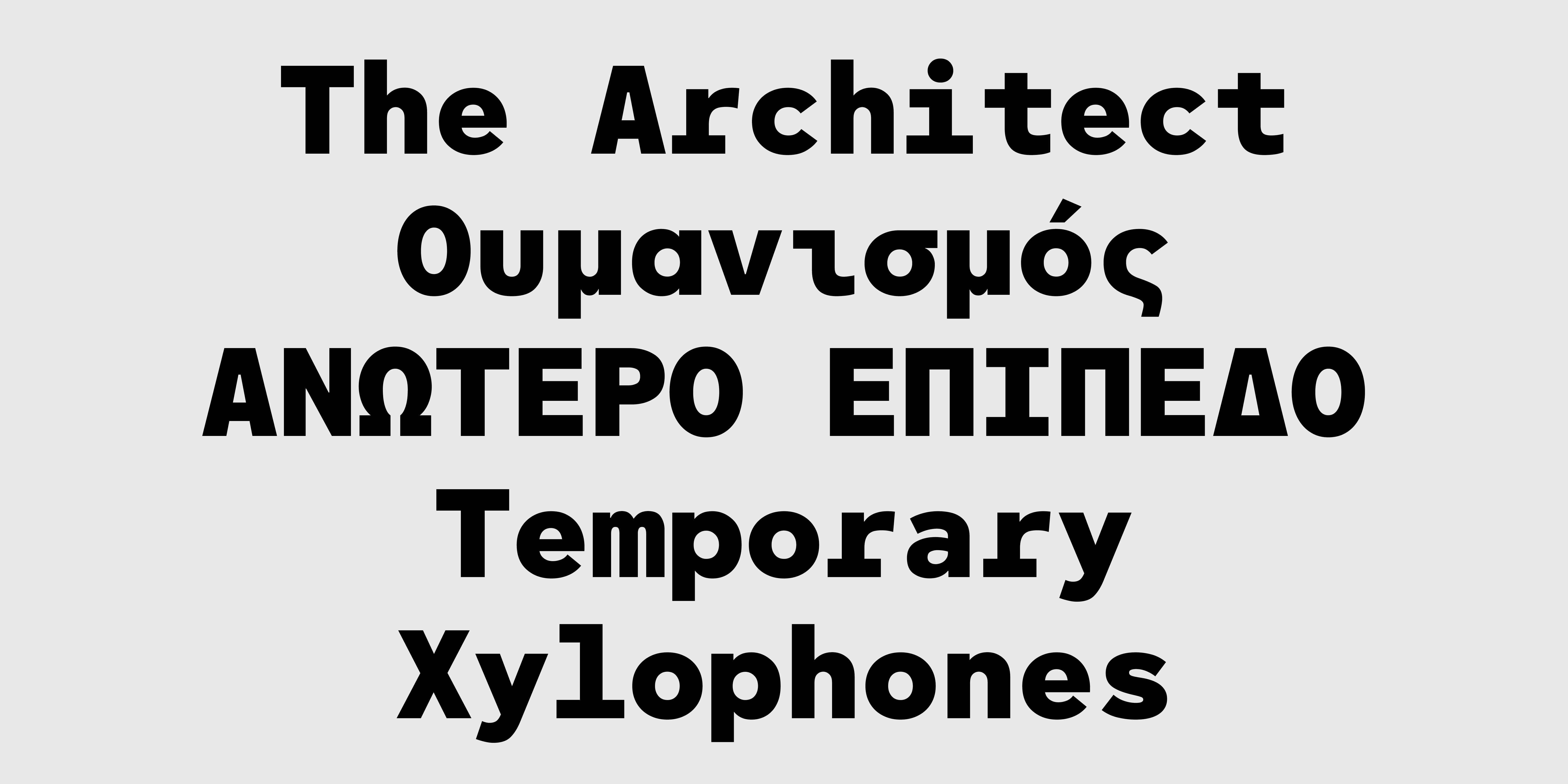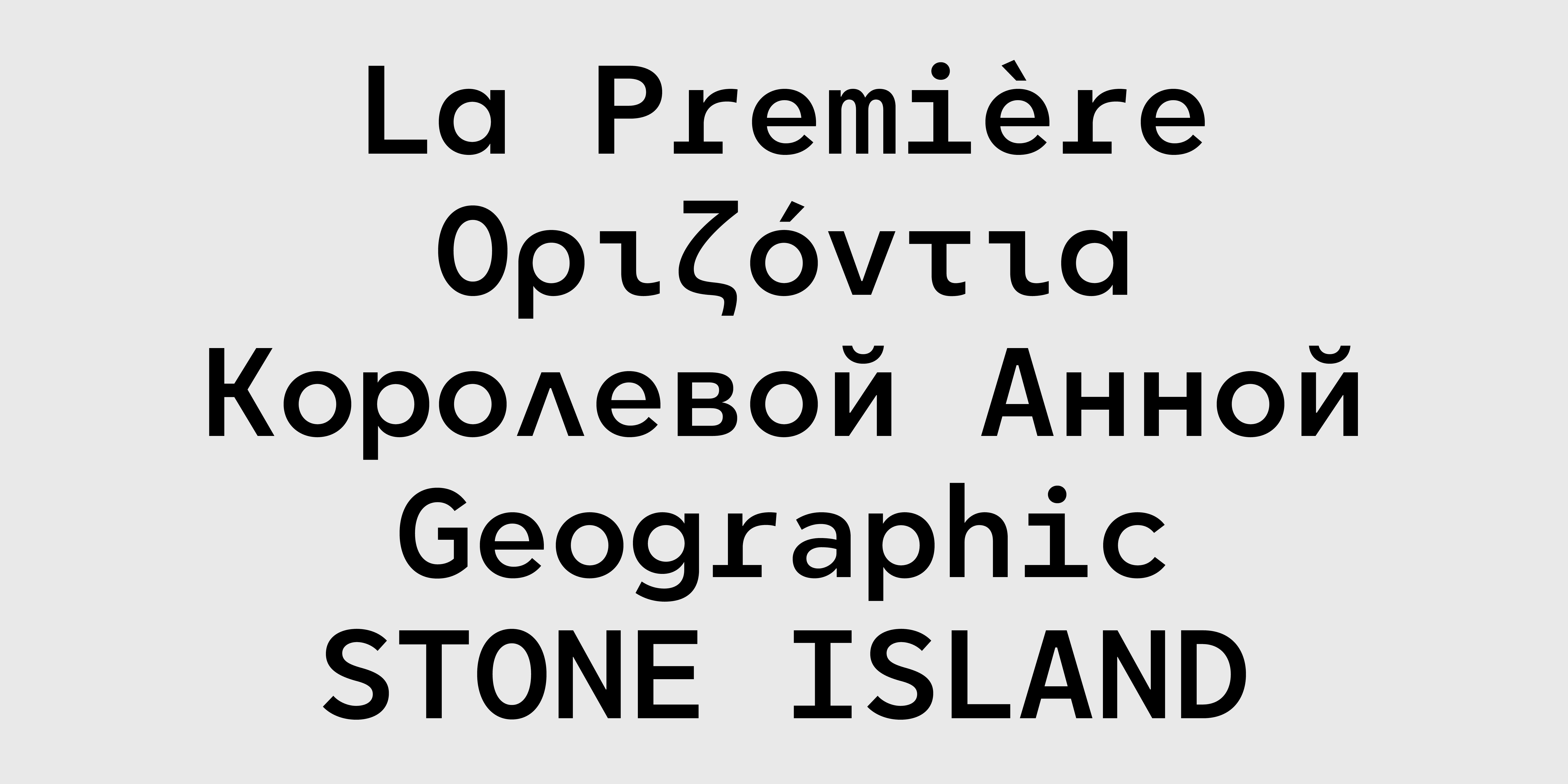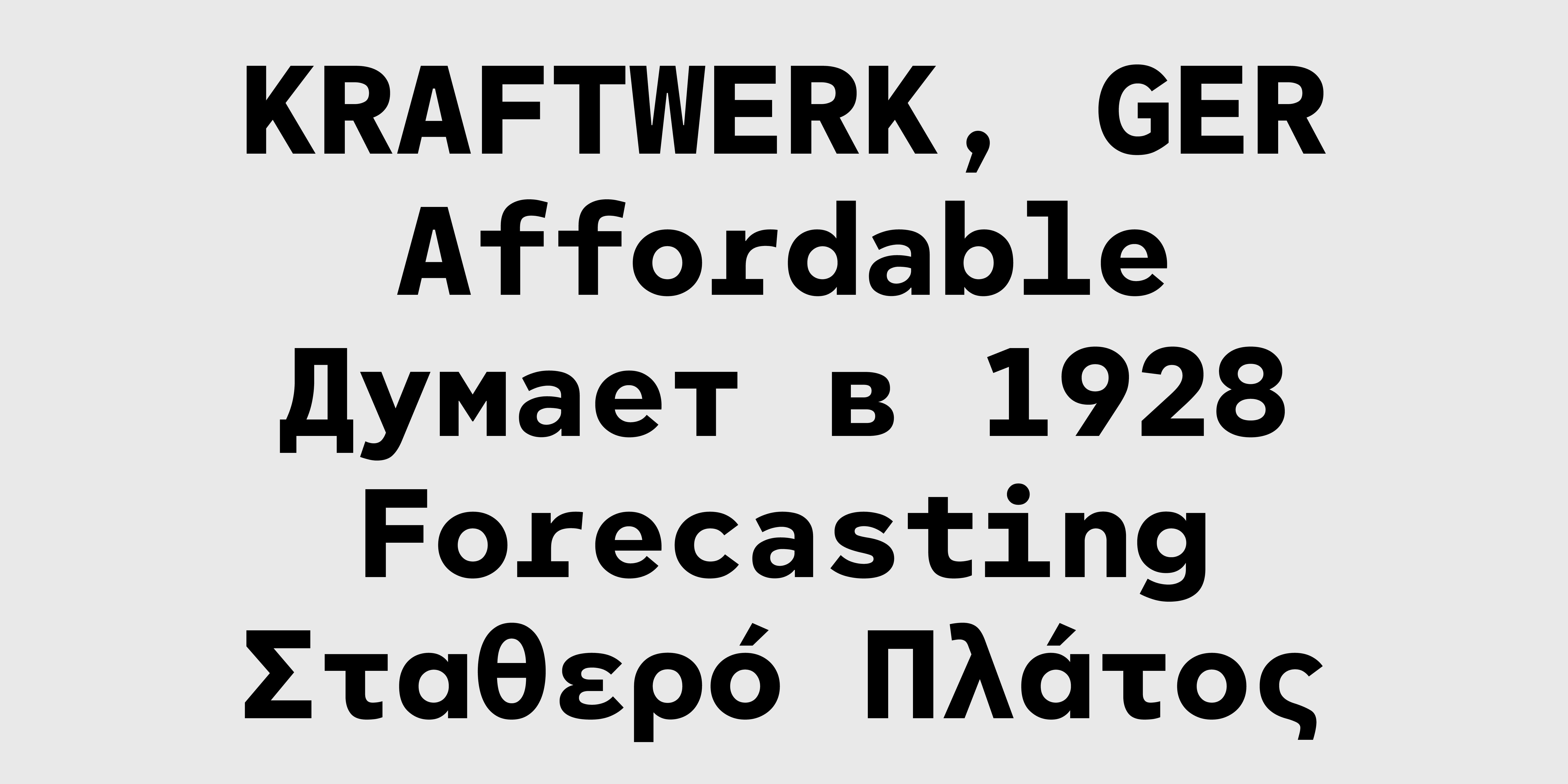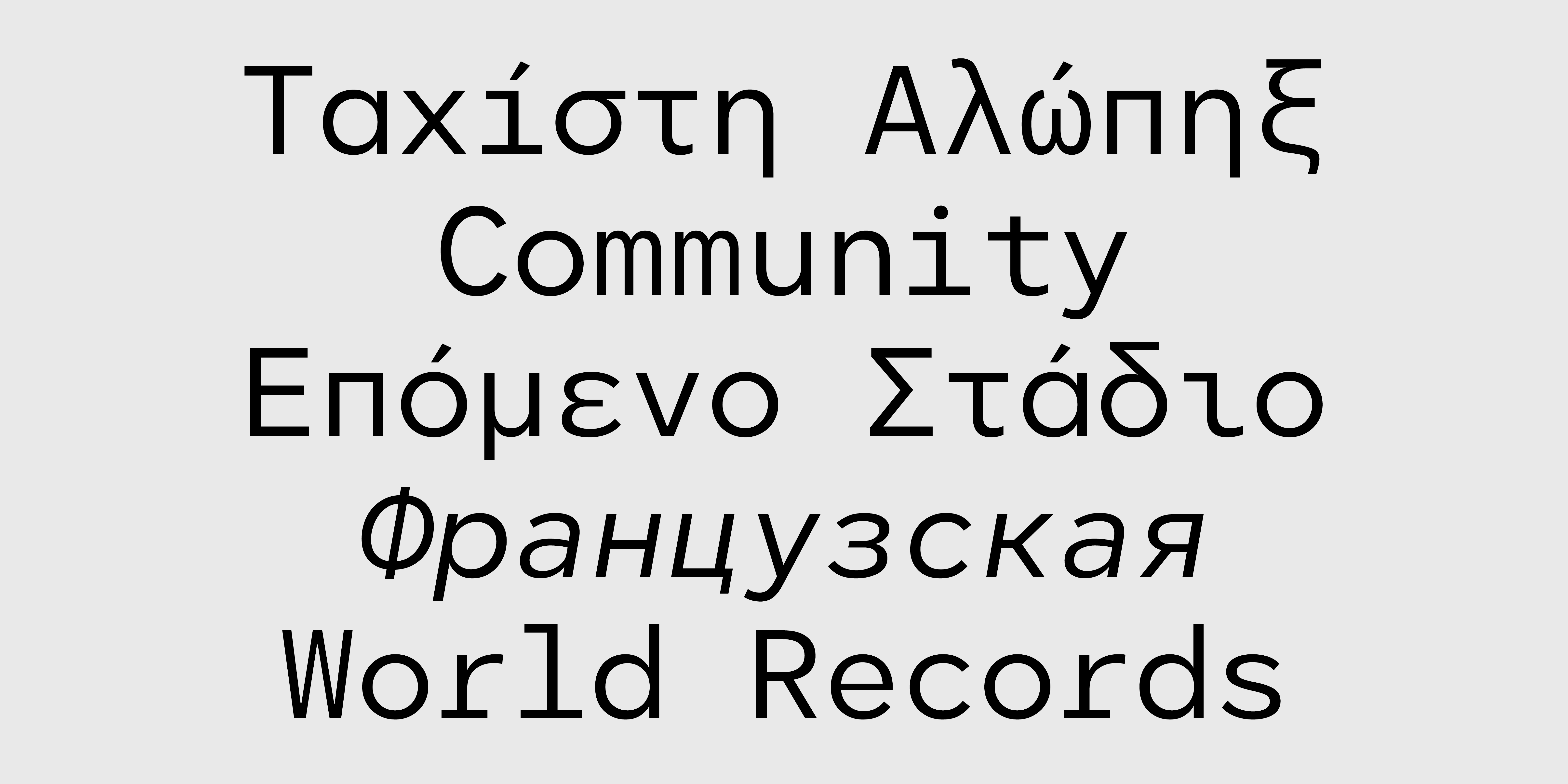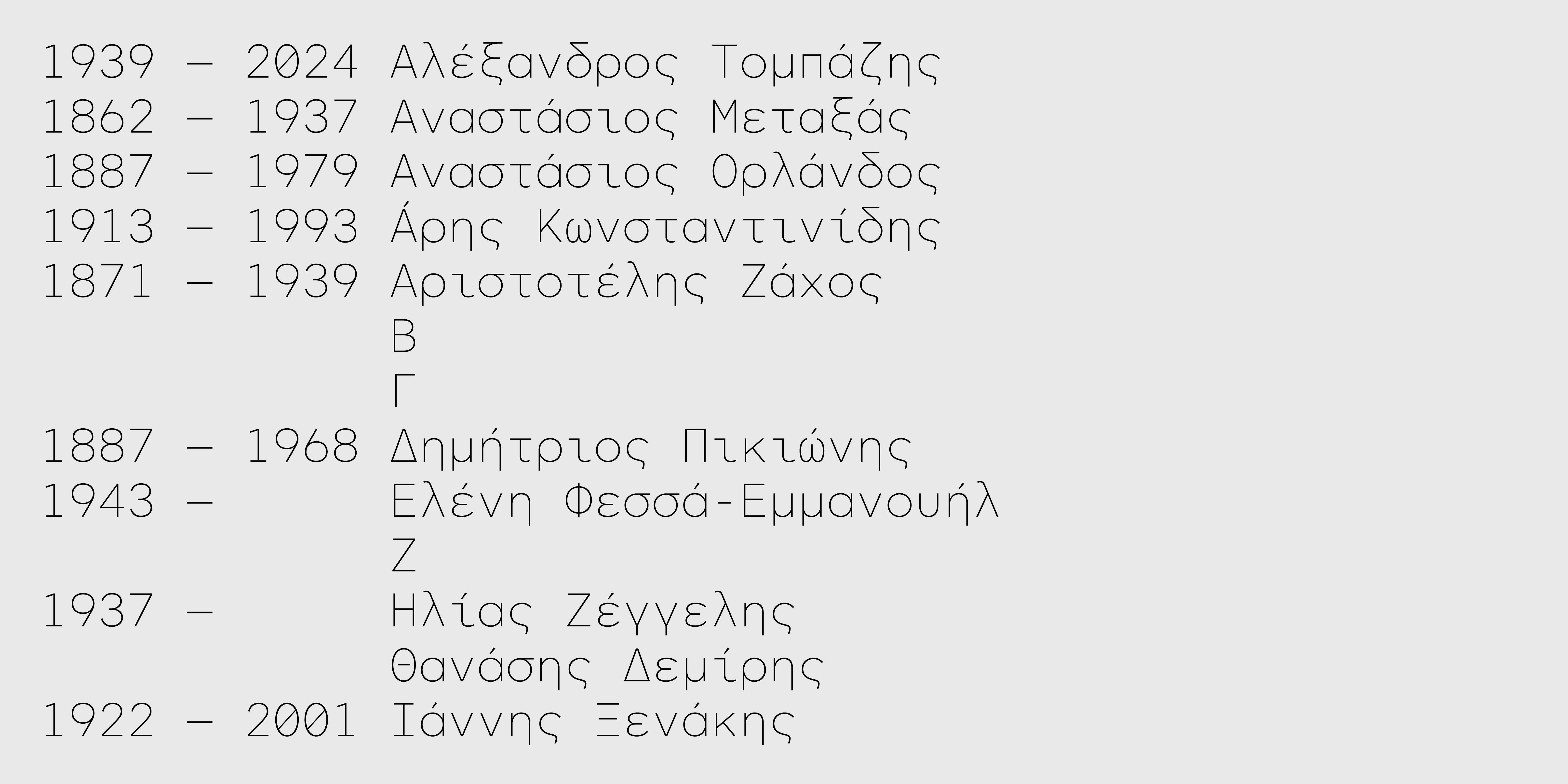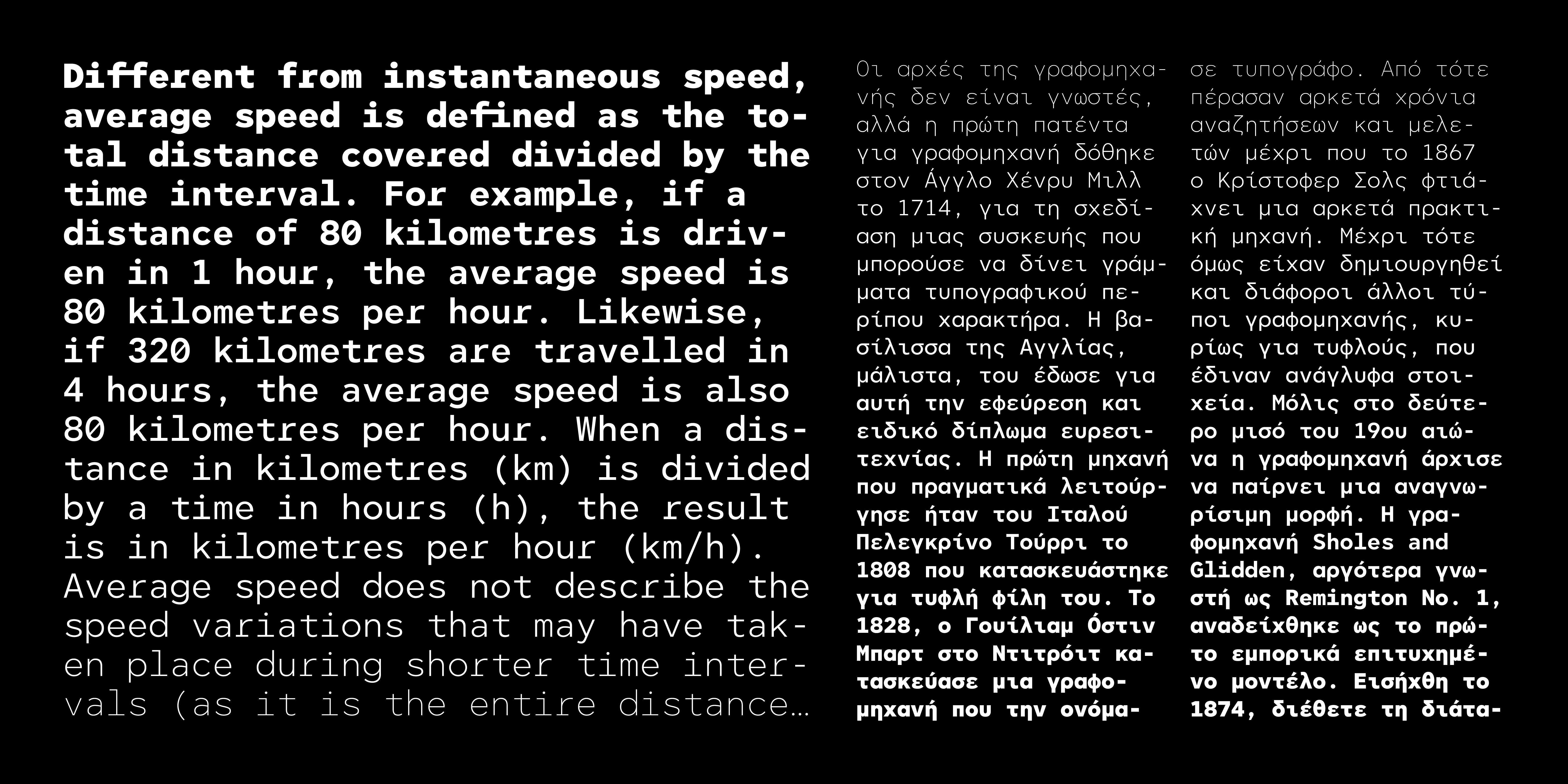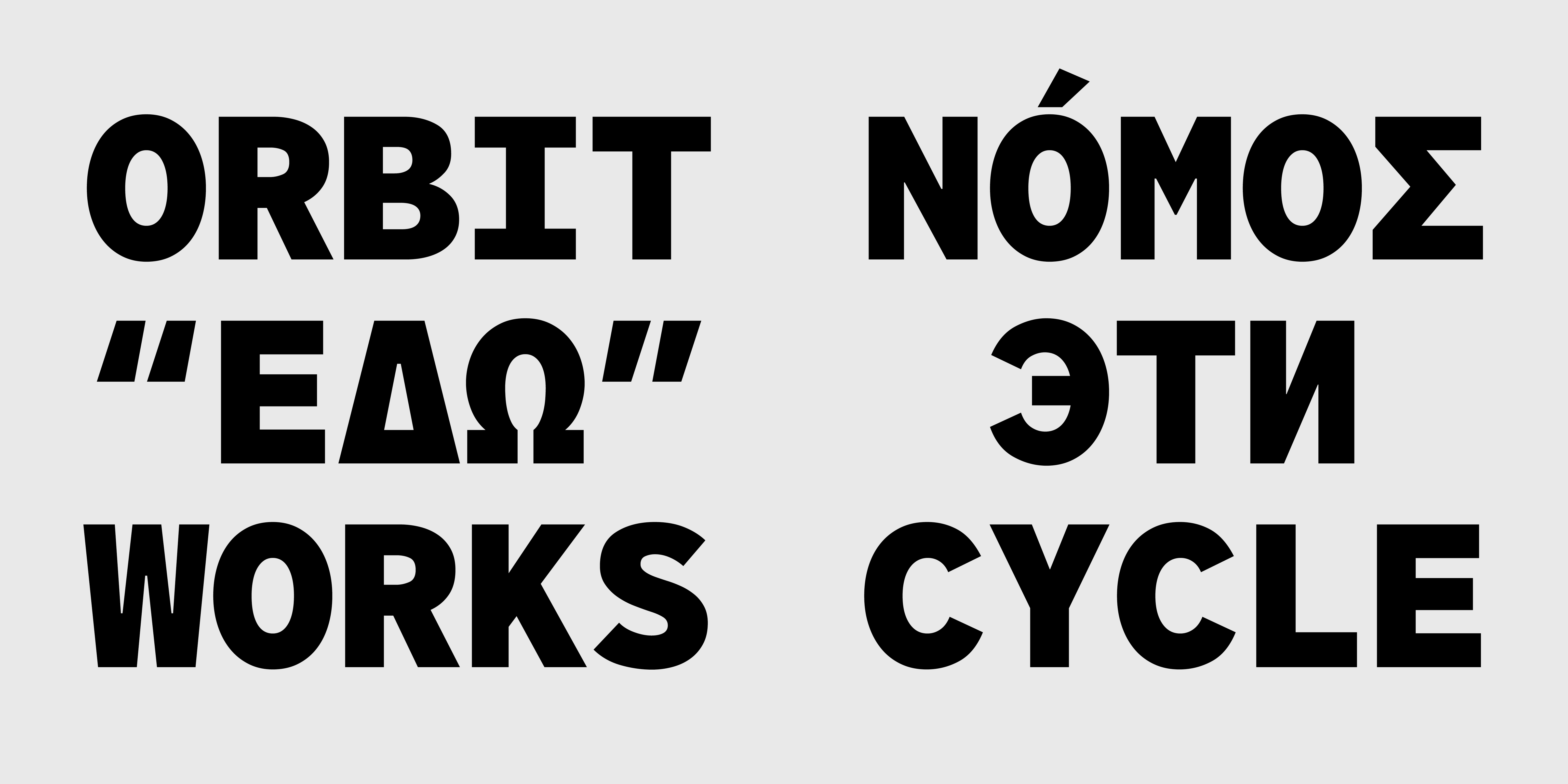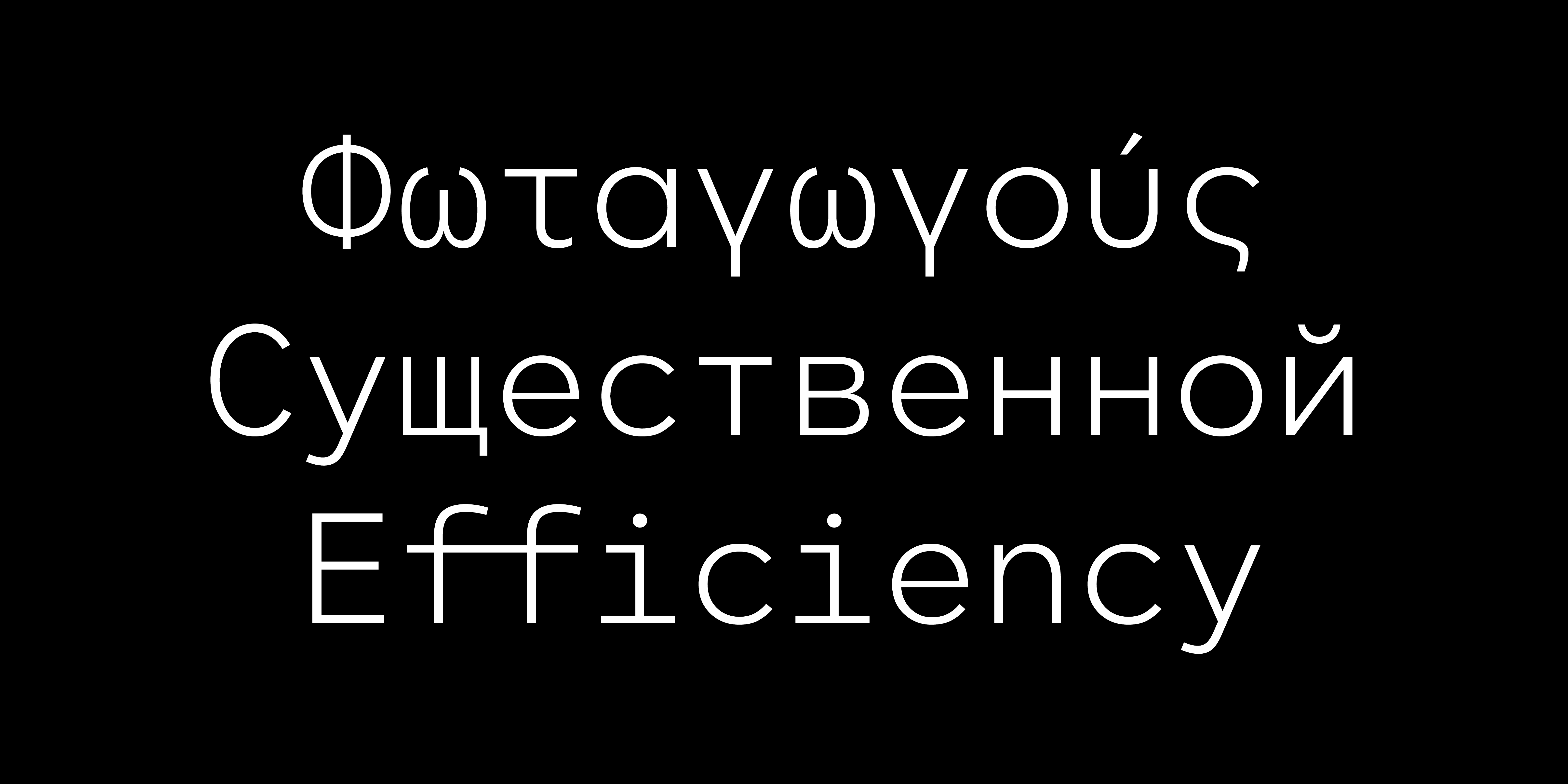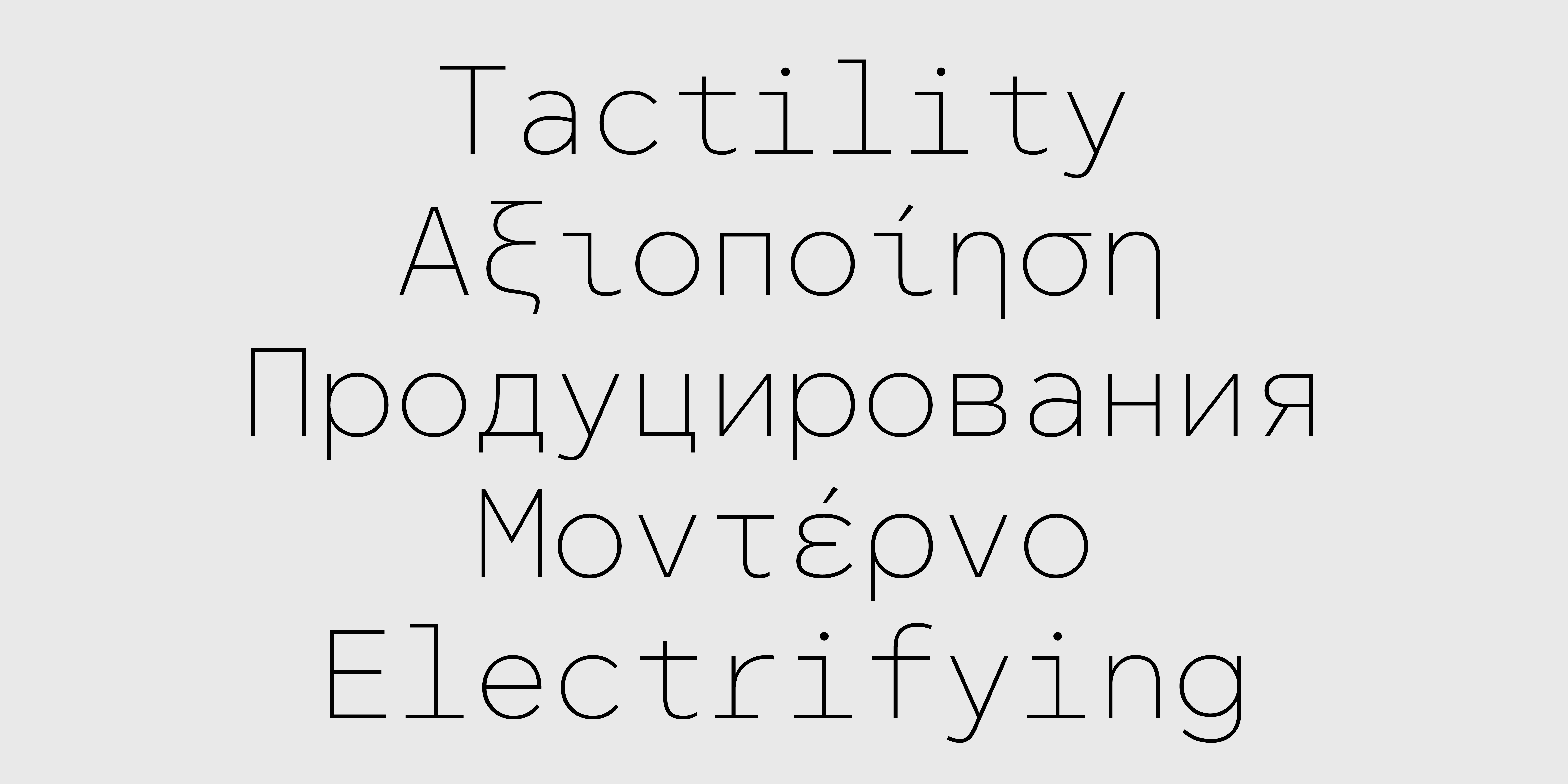
Asty Monospaced Collection
Asty Monospaced
Thin Thin Oblique Light Light Oblique Regular Oblique Medium Medium Oblique Bold Bold Oblique Black Black ObliqueΗ πολύ δημοφιλής γραμματοσειρά CF Asty διαθέσιμη σε έκδοση σταθερού πλάτους (monospaced). Το σχέδιο έχει προσαρμοστεί με σκοπό να προσδώσει μια digital αισθητική, απαραίτητη για χρήσεις όπου απαιτείται μοντέρνα, ψηφιακή ή και φουτουριστική αίσθηση. Παράλληλα, με την κατάλληλη αυξομείωση του πλάτους των χαρακτήρων μέσα στο προκαθορισμένο χώρο που εντάσσεται ο καθένας, μειώνονται τα κενά και οι αντιφόρμες που προκύπτουν από την έλλειψη kerning με σκοπό να βελτιωθεί η ευαναγνωσιμότητα σε μεγαλύτερα κείμενα. Η CF Asty Mono υποστηρίζει Greek, Western, Extended Latin καθώς Cyrillic character sets ενώ είναι διαθέσιμη και σε Variable αρχείο χωρίς επιπλέον χρέωση.